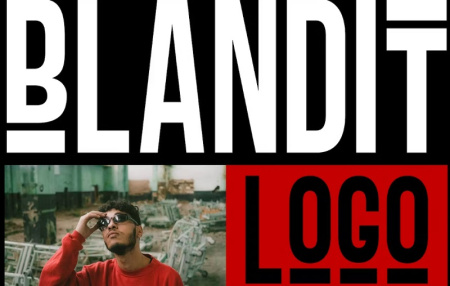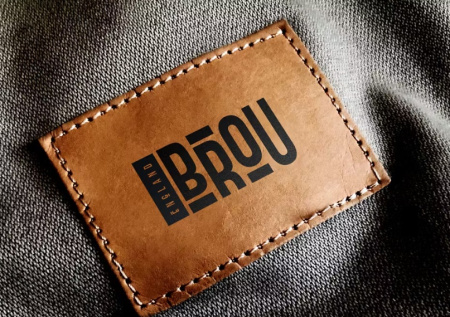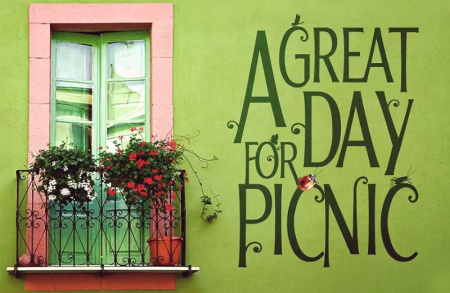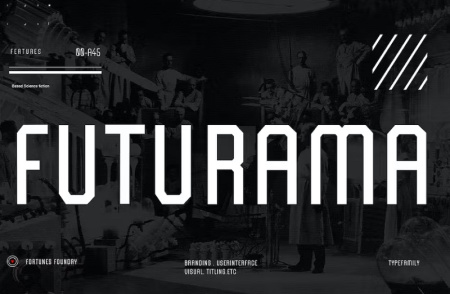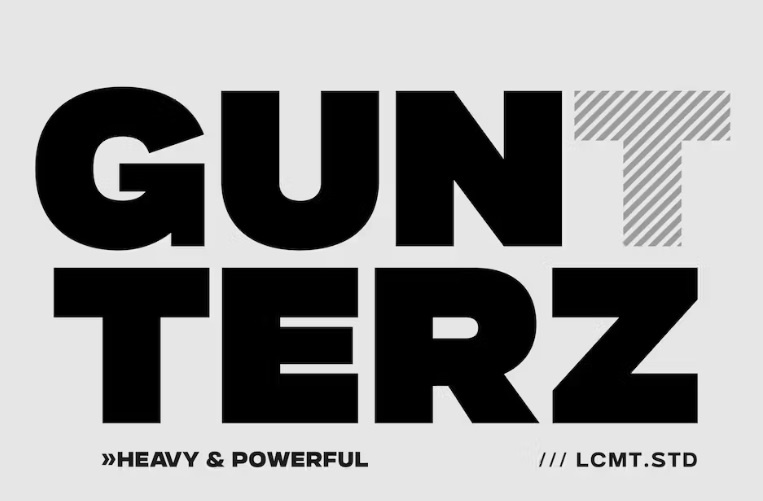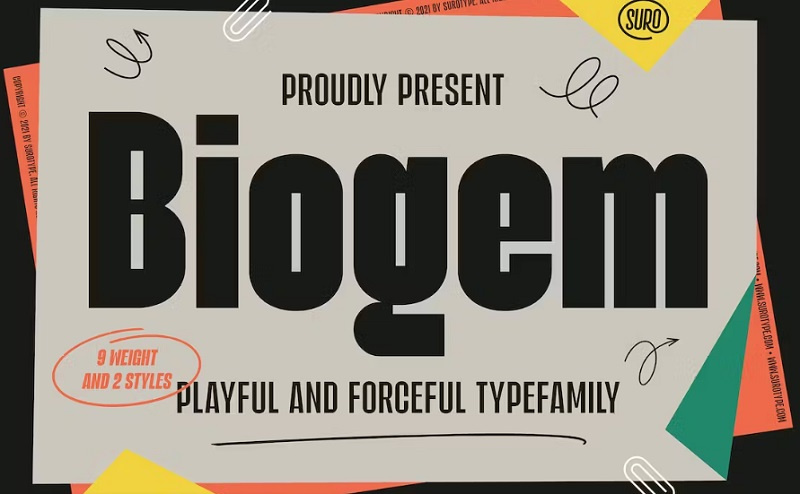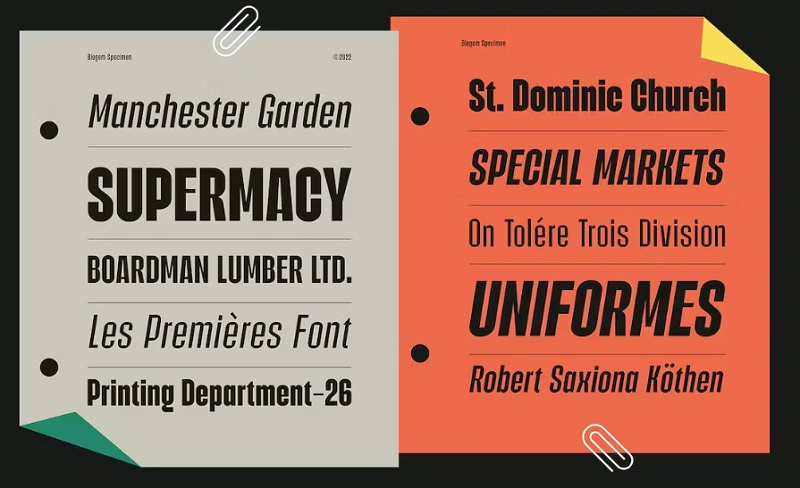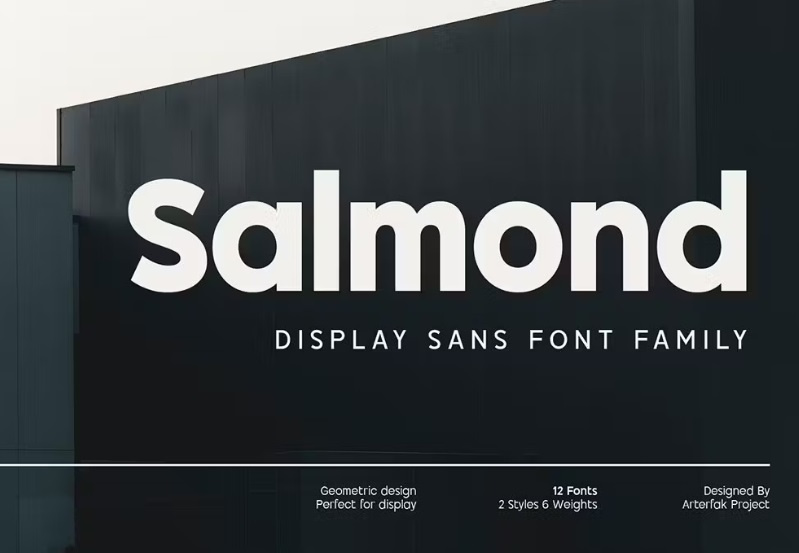
فونت انگلیسی تیتر⭐دانلود 6 فونت انگلیسی مناسب تیتر Modern Titling
فونت انگلیسی تیتر و عنوان از جی اف ایکس دانلود. این مجموعه شامل 5 فونت انگلیسی مناسب تیتر می باشد. فونت انگلیسی تیتر مناسب برای طراحی لوگوهای مینیمالیستی، عناوین، برچسب ها، پوسترهای فیلم، سرفصل ها، عنوان ، طرح های لوگو، بنرهای بزرگ هستند. در ادامه می توانید پرطرفدارترین فونت های انگلیسی برای تیتر و عنوان را مشاهده و دانلود نمایید.
2- بهترین فونت انگلیسی تیتر
اگر دوست دارید یک فونت قدرتمند و جسورانه برای سرفصل و تیترها داشته باشید، بهترین فونت انگلیسی تیتر با نام Gunterz می تواند انتخاب خوبی شما باشد. دانلود فونت انگلیسی برای تیتر مناسب برای عناوین پوستر، طراحی بسته بندی، سرفصل ها، لوگوتایپ ها، موشن گرافیک، عناوین فیلم، تبلیغات ورزشی و فناوری آینده مناسب است.
3- فونت انگلیسی مناسب تیتر
فونت انگلیسی مناسب تیتر با نام Biogem از جی اف ایکس دانلود برای شما کاربران عزیز در سایت قرار داده شده است. این فونت تیتر انگلیسی با فایل های OTF +TTF و Woff2 ارائه شده است.
4- دانلود فونت انگلیسی تیتر
Salmond یک فونت انگلیسی برای تیتر و عنوان به سبک مدرن و مینیمال می باشد. شامل شش سبک مختلف از جمله وزن سبک، معمولی، اخبار، متوسط، نیمه پررنگ، و پررنگ است. این فونت برای نیازهای مختلف طراحی مناسب می باشد.